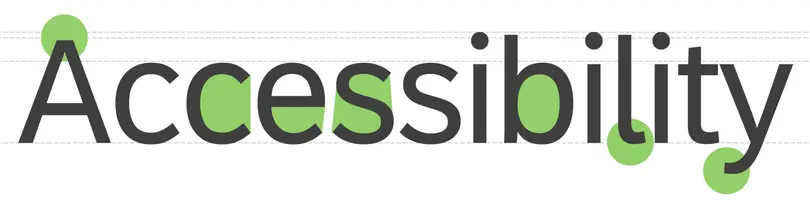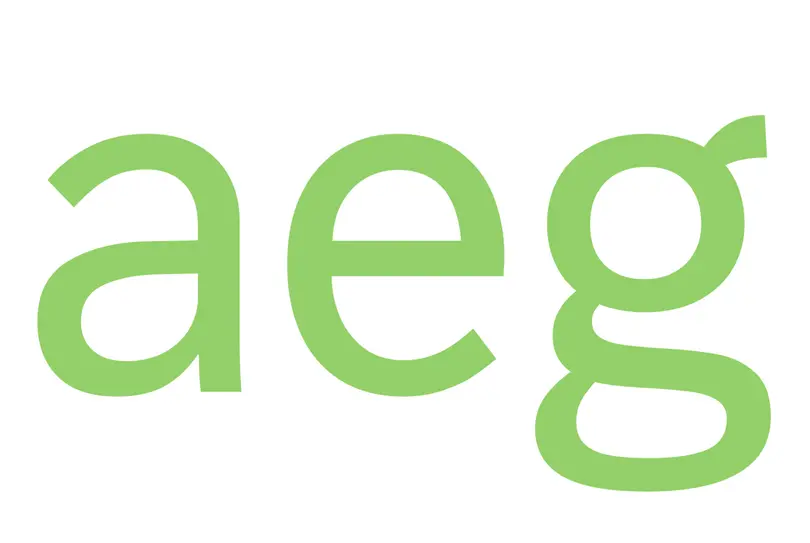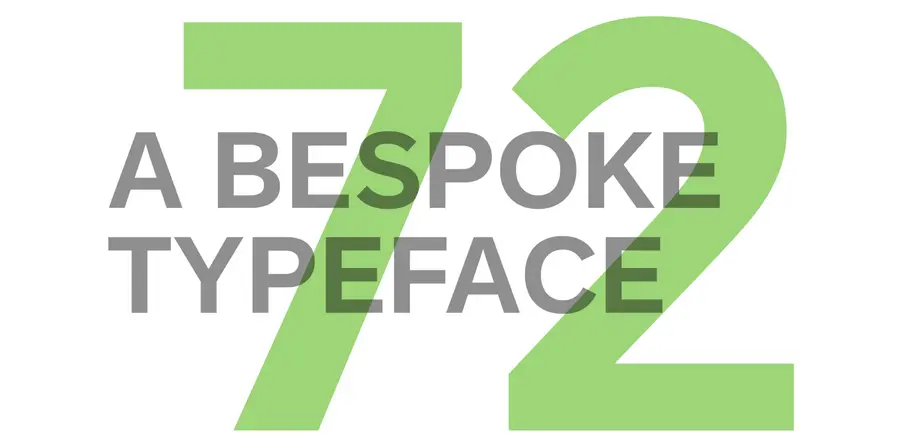
Criação da fonte para a SAP Fiori.
“ Ele é amigável ao mesmo tempo que trabalha forte, o que é exatamente o que um aplicativo da Fiori deveria fazer. ”
Terrance Weinzierl da Monotype ajudou a empresa de software SAP a desenvolver uma fonte para a SAP Fiori, pela qual a SAP ganhou um Red Dot Award em 2015. Era importante que o design da fonte funcionasse bem em ambientes de UI baseado em texto sem comprometer a personalidade. A nova fonte, chamada 72, ganhou um Red Dot Award em 2017.
Com o lançamento da SAP Fiori, a empresa precisava de um conjunto de fontes capaz de oferecer uma hierarquia tipográfica e auxiliar usuários a navegarem por telas repletas de textos. Tendo em vista que a interface de usuário era composta quase que exclusivamente por texto, era essencial que as fontes funcionassem de maneira confortável em uma grande variedade de telas.
“Uma boa fonte e tipografia desempenham função significativa em UI, por mais que isso passe despercebido pelo usuário a maior parte do tempo”, disse Jeong-Sook Lee, da SAP. “Um bom sistema tipográfico cria uma hierarquia visual clara ao empregar o equilíbrio perfeito entre diferentes tamanhos, pesos e estilos. Uma bela fonte com grande legibilidade em qualquer escala em diferentes pesos e estilos era o que precisávamos para nossa UI.”
Além de todos os requisitos técnicos, era fundamental que a fonte equilibrasse desempenho e estilo, capaz de desempenhar bem em termos de legibilidade, escalabilidade e acessibilidade, enquanto comunicava a voz da SAP com clareza.
Trust
“Diante de tantos produtos digitais, a experiência é a marca”, explica John Pompa, da SAP. “Nossos usuários precisam consumir este conteúdo sem dificuldades”, complementa. “Não podemos permitir que o design atrapalhe as pessoas de operarem de maneira eficaz.”
Em busca de uma substituta para a fonte Arial padrão, SAP e Terrance Weinzierl, da Monotype, se encontraram para discutir estilos de fonte que poderiam comunicar o conteúdo como confiável enquanto enfatizavam uma sensação de cordialidade e simpatia.
aeg
“ Ele é amigável ao mesmo tempo que trabalha forte, o que é exatamente o que um aplicativo da Fiori deveria fazer.” ”
“Tínhamos em mente esse conceito de fontes neogrotescas como Arial e Helvetica que representam algo sério e verdadeiro, mas precisávamos evitar sermos muito frios ou sem graça”, explica Weinzierl, que ajudou a SAP a observar um espectro completo de fontes grotescas, humanistas e góticas. “Foi a combinação de algo que parecia sério, mas ainda levava consigo o suficiente do conceito da SAP Fiori, que é tornar algo amigável ao consumidor. Foi aí que encontramos o ponto ideal.”
Weinzierl começou pelo desenho do a e g em caixa baixa, letras “notórias” por conterem muito do DNA do design. Ambas as formas fazem a referência de um g da Trade Gothic, e contam com aquilo que Weinzierl chama de “orelhão elástico”.
“Penso até mesmo uns detalhezinhos como esses, dentro daquela estrutura grotesca, podem conferir vida ao material”, explica. “Suponho que essa seja parte difícil do design de fontes. Se um conjunto de detalhes for demais, acaba mudando o tom de tudo muito rápido, porque aquele detalhe se repete dezenas de vezes em uma página. É uma questão de ser sutil mesmo.”
Levando cerca de quatro meses até sua conclusão, o processo de design envolveu uma série de reuniões entre as equipes de design da Monotype e SAP, com letras revisadas repetidamente para que atendessem aos requisitos. A SAP 72 precisava ser trabalhada dentro das métricas da Arial, enquanto mantinha sua própria personalidade através de caracteres mais arredondados e uma altura x um pouco maior.
Accessbility
“Ela tem a sinceridade neogrotesca com a energia humanista de uma fonte gótica”, adiciona Weinzierl. “É amigável enquanto dá duro, o que é exatamente o que um aplicativo da Fiori deveria fazer.”
Ascendentes e descendentes são proporcionalmente iguais, de forma a obter um alinhamento vertical centralizado através de CSS dentro dos controles da UI, além disso, houve foco para tornar as letras facilmente distinguíveis, por exemplo, ao criar um contraste claro entre o I em caixa alta e o L em caixa baixa. A fonte foi otimizada para telas e tamanhos pequenas, adicionalmente. A fonte também oferece suporte linguístico completo para línguas europeias de forma a refletir a diversidade de mercados nos quais a empresa opera.
O desenvolvimento da fonte foi uma oportunidade para um diálogo mais amplo acerca da função desempenhada pelas fontes dentro da SAP enquanto empresa, e como estas refletem sua personalidade.
“O design está se tornando parte central da SAP”, comentou Pompa. “Enquanto organização, há um valor atraente nisso, e na forma como a SAP quer se posicionar, logo, a 72 é uma contribuição significativa.”
Como Diretor Criativo de Tipografia no Monotype Studio, Terrance Weinzierl vem criando e modificando tipos para a Biblioteca Monotype e uma ampla gama de marcas desde 2008. Além de trabalhar em projetos personalizados para PBS, Microsoft, Google, Barnes & Noble, Domino’s e SAP, ele desenvolveu tipos para videogames, equipes esportivas profissionais e fabricantes de automóveis.